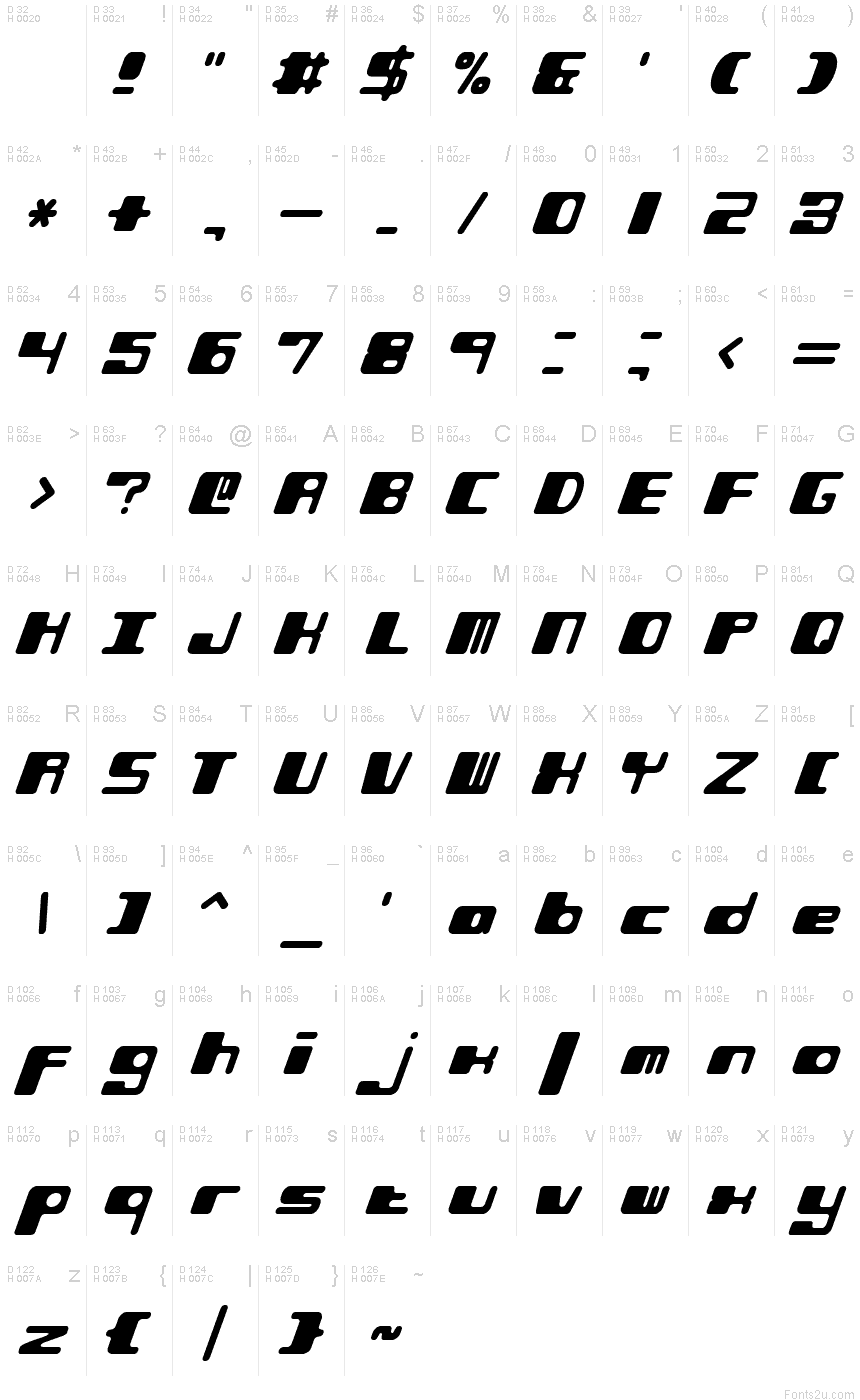
Phorfeit Slant di ÆNIGMA Fonts è un font display futuristico e gratuito, dal carattere veloce e progettato su misura. Le lettere si inclinano in avanti con forme spesse e arrotondate; il mix di angoli morbidi e giunture nette conferisce al testo un aspetto aerodinamico, compatto e un po' sintetico.
È perfetto per loghi di gaming, flyer tech, poster per club, titoli e copertine che richiedono un font gratuito dinamico, senza però ricorrere ai soliti cliché sci-fi. Poiché le forme rimangono larghe e semplificate anche nell'inclinazione, funziona bene anche per branding breve, intestazioni di app e qualsiasi altro impiego display che necessiti di una spinta audace verso il futuro.